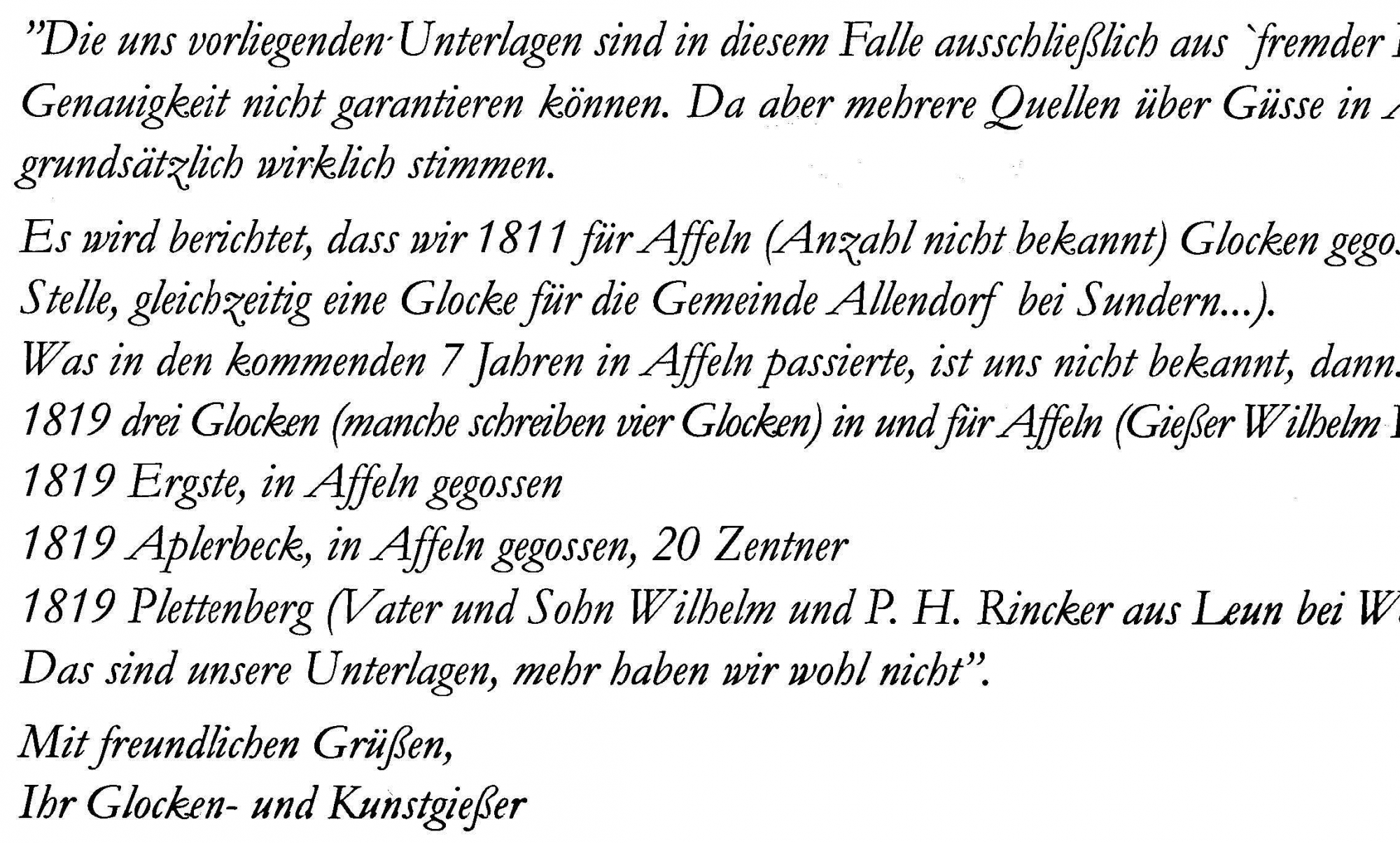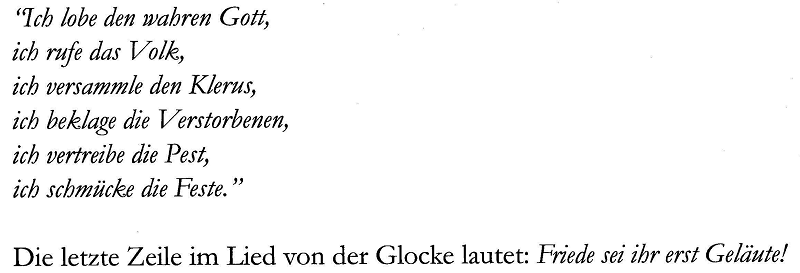
Großbuchstaben nicht kursiv, sondern nur schräg?
ich bekam heute ein recht amateurhaft gesetztes Buch (mit sehr lokalem Inhalt), bei dem in den kursiven Passagen die Großbuchstaben nicht aus dem kursiven Schnitt stammen, sondern aus dem aufrechten Schnitt schräggestellt.
Vor einigen Jahren fiel mir dieser Effekt auch bei einer Korrekturfahne auf, er trat dann aber im Druck nicht mehr auf.
Was passiert da? Gibt es ein Problem zwischen Satz und Druck?
Diese Buchstaben heißen als Stil oblique. Leider werden bei Fonts, die nicht richtig miteinander verknüpft sind, von Textprozessoren die Buchstaben nur "schräg gelegt", wenn sie keine echten Kursiven finden. Die Information, dass ein entsprechender Abschnitt kursiv dargestellt werden soll, geht jedoch nicht verloren. Wenn auf einem anderen Computer die Fontfamilie heil ist, klappt alles so wie beabsichtigt.
Ist ein häufiges Problem bei lieblos zusammengeklickerten Fonts oder auch bei Fonts, die aus dubiosen Quellen stammen.
Kann ein Font denn so „kaputt“ sein, dass die Kleinbuchstaben korrekt kursiv dargestellt werden und nur die Großbuchstaben nicht?
Hast du nur das gedruckte Buch gesehen und schließt diese Vermutung aus den unterschiedlichen Schrägstellungen?
Manche Schriften – gerade frühere Garamonds – haben fast gerade Versalien, die mit den Gemeinen scheinbar nichts zu tun haben*. Vielleicht ist das so eine Schrift. Dass da technisch mit Versalien anders als mit Minuskeln umgegangen wird, halte ich für unwahrscheinlich.
Das sieht mir sehr nach so einer Garamond-artigen Schrift aus, die Schnitzel schon beschrieben hatte.
Manche Schriften – gerade frühere Garamonds – haben fast gerade Versalien, die mit den Gemeinen scheinbar nichts zu tun haben
Das Q sieht schon mal nach einem echten kursiven aus. Da wurde nichts künstlich (zu wenig) schräg gestellt.
Stimmt! Das scheint die gleiche Garamond zu sein, die irgendwann bei Windows mitgeliefert wurde (meine ist V2.40 von Monotype).
Und aus Traditionsgründen wurde diese Ungleichheit so beibehalten..? :shock:
Is halt was für Traditionalisten. Die meisten modernen Digital-Garamonds haben diese Merkwürdigkeit ja schön weichgespült.